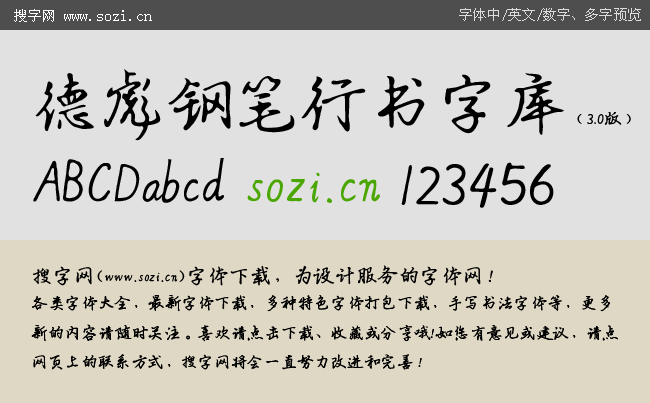
德彪鋼筆行書字庫(更新)
搜字網(wǎng)提供一款德彪鋼筆行書字庫(更新)中文書法字體下載。德彪鋼筆行書是一款應(yīng)用于設(shè)計方面的手寫風格硬筆書法中文字體,字形奔放,瀟灑大方,此款為更新版,調(diào)整了小字號顯示的清晰度,另外增加和修改了142字,可用于平面設(shè)計、印刷包裝、廣告設(shè)計、藝術(shù)繪畫等行業(yè)領(lǐng)域。